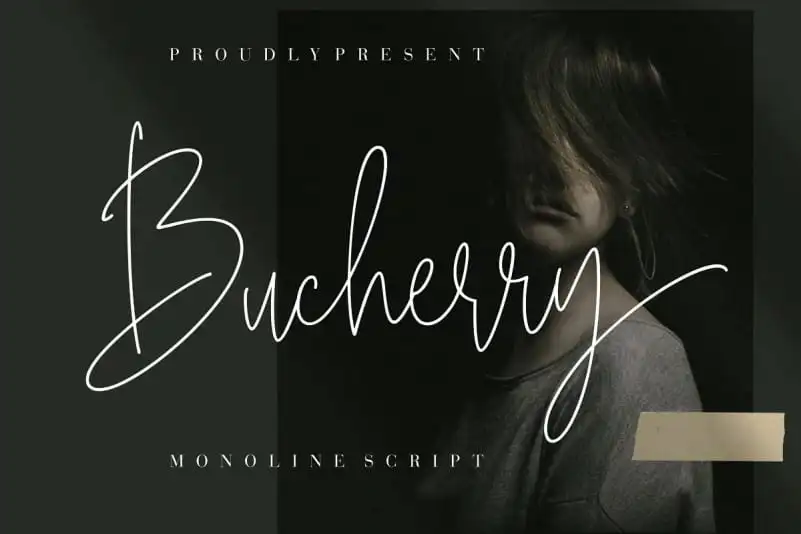
Bucherry Handwritten Font – Download Grátis
Bucherry Handwritten Font é uma nova fonte criada pela Creatype Studio com traços suaves e estilo de calligrafia luxuosa. Esta fonte é perfeita para projetos de marca, logomarca, designs de casamento, postagens nas redes sociais, anúncios, embalagens de produtos, design de produtos, rótulos, fotografia, marcas d’água, convites e materiais de papelaria. Suas formas curvas fluidas oferecem um toque autêntico que é perfeito para adicionar personalidade e elegância aos seus projetos digitais. Independentemente do tipo de projeto em que seja utilizada, Bucherry garante que seu texto apareça com uma sensação única e agradável, tornando-a ideal não só para designers gráficos experientes, mas também para aqueles iniciantes que buscam um toque sofisticado em seus projetos.